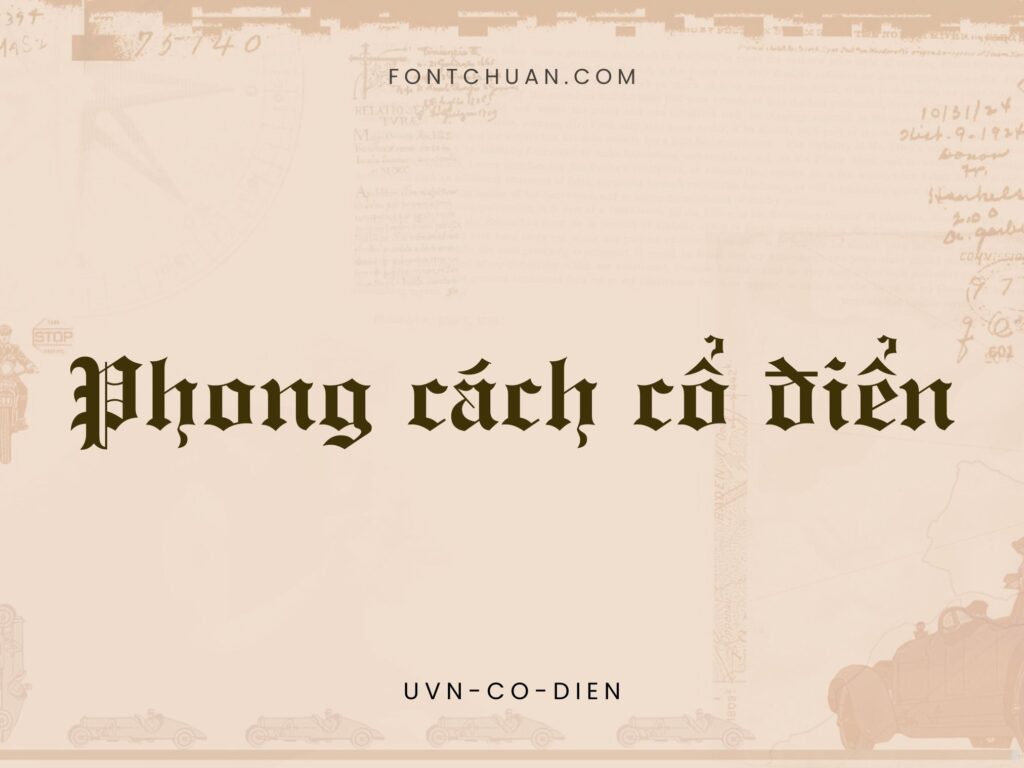
Font UVN Co Dien Việt Hóa
UVN Cổ Điển là một font chữ serif cổ điển mang đậm nét truyền thống và hoài niệm, thường thấy trong các ấn phẩm mang tính văn hóa, lịch sử hoặc những thiết kế cần sự trang trọng. Với phong cách tinh tế, kiểu chữ này tạo nên cảm giác uy tín và chiều sâu trong cách thể hiện nội dung. Font này được thành viên Font Chuẩn chọn lọc và sưu tầm để ứng dụng trong các dự án yêu cầu độ chuẩn xác và thẩm mỹ cao, nhất là khi kết hợp với nội dung mang tính di sản.
UVN Cổ Điển có hệ thống chân chữ rõ ràng, tỷ lệ chữ cân đối và các chi tiết gãy gọn mang tính thẩm mỹ cổ xưa. Font phù hợp để sử dụng trong sách lịch sử, tiêu đề tài liệu truyền thống, thiết kế bìa sách hoặc các ấn phẩm lễ hội mang tính cổ truyền. Những ngành nghề phù hợp bao gồm giáo dục, bất động sản, quảng cáo, công nghệ và thiệp cưới. Font cũng thích hợp sử dụng cho các sự kiện như Tết, ngày Nhà giáo, lễ hội và Trung thu.